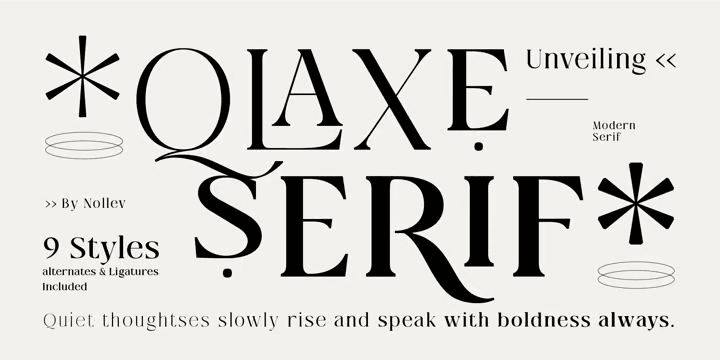
Qlaxe Serif
品の良いクラッシーなディスプレイローマン。ややコンデンスめでゆったりしたカウンターを持つグリフに、コントラスト強めのストロークで決めた書体。セリフは基本かなり小さめだが、F のビーク(くちばし)などは大きめになっているのが特徴。ご多分に漏れず、美しいスワッシュオルタネートやユニークなリガチャーが多数あり。この手としてはめずらしくファミリー展開されており、9ウェイトもあるのが魅力。ただいま30%オフセール中。